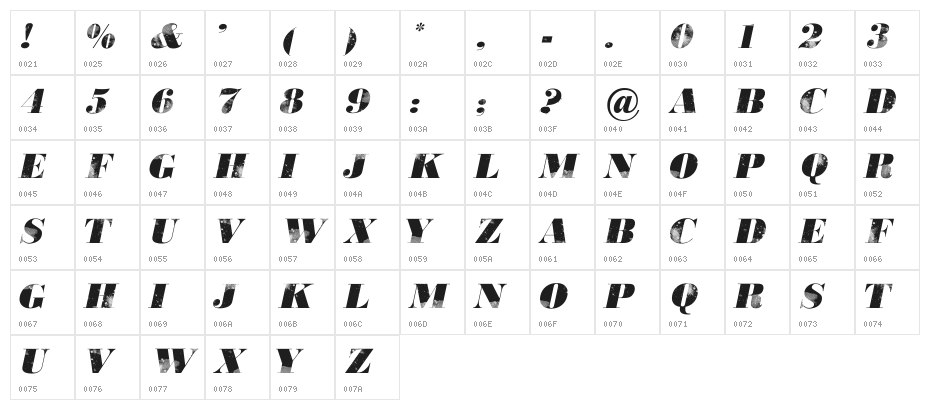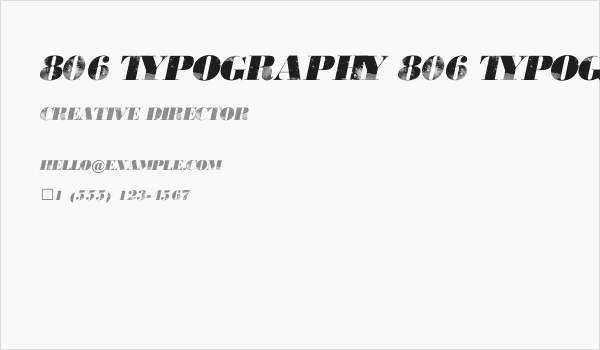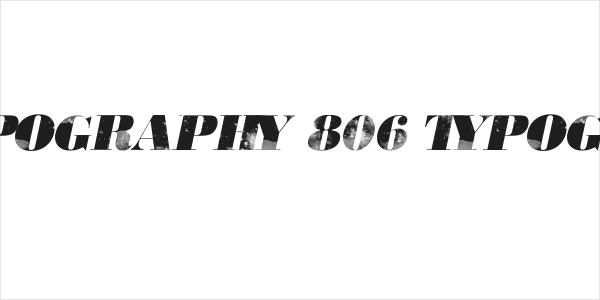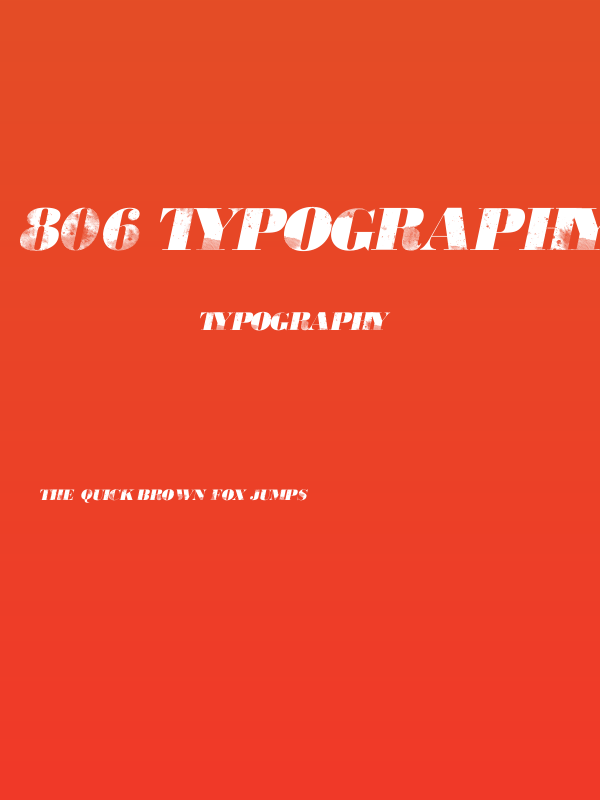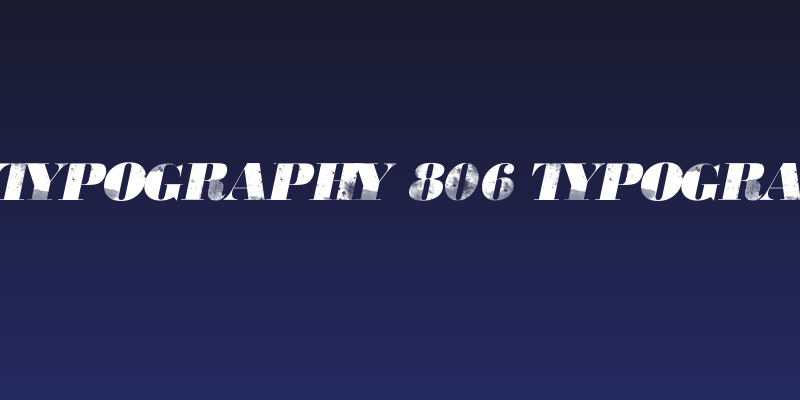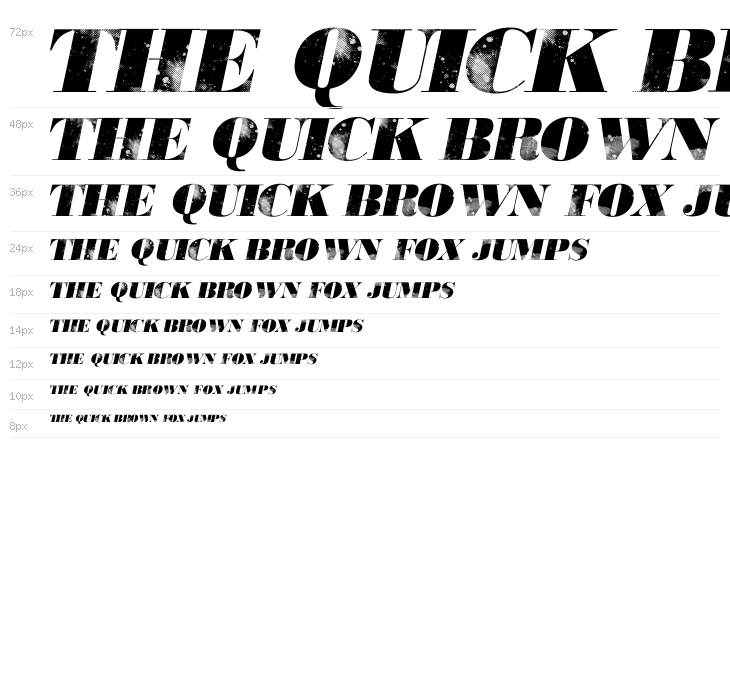
806 Typography 806 Typography Font
✎ Distorted Eroded
| Stile generale | Modern, Edgy |
| Progetti proposti | Ideal for posters, album covers, branding, and any project needing a bold, artistic touch. |